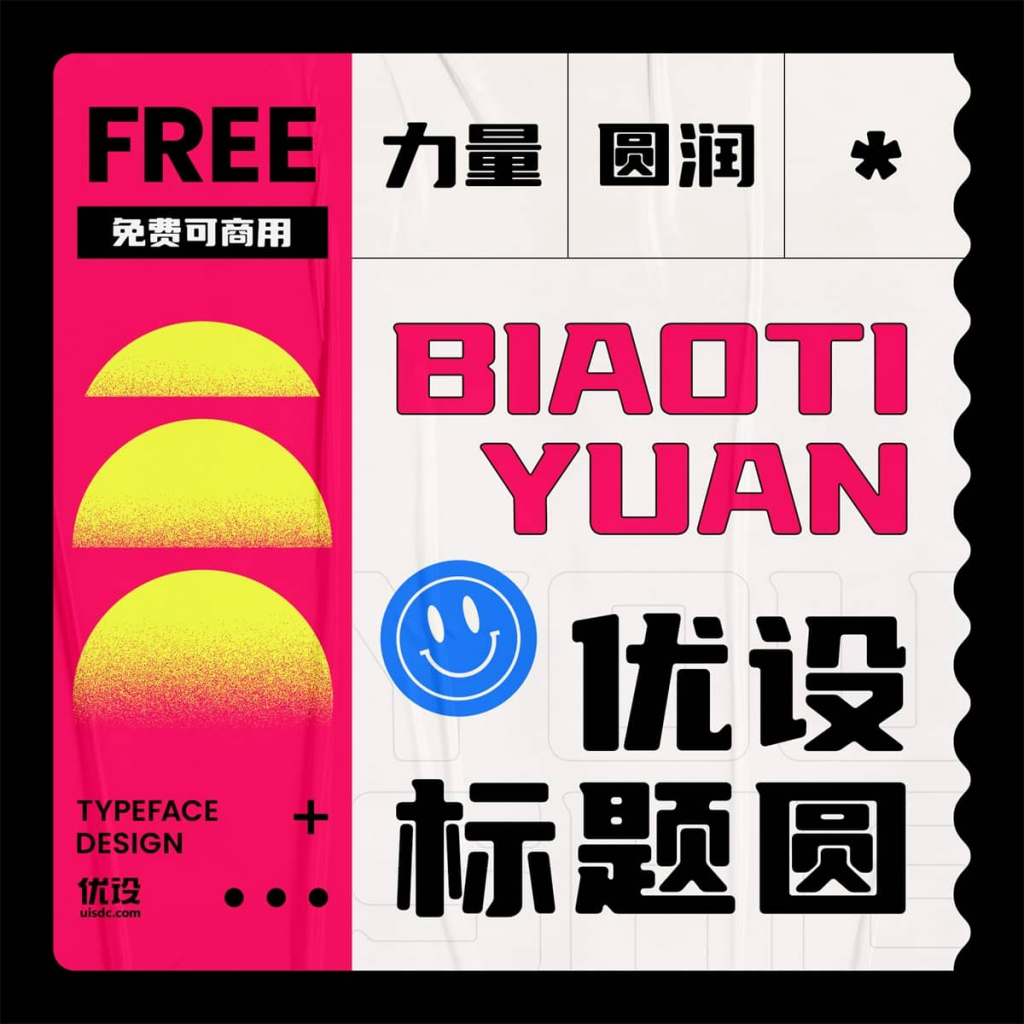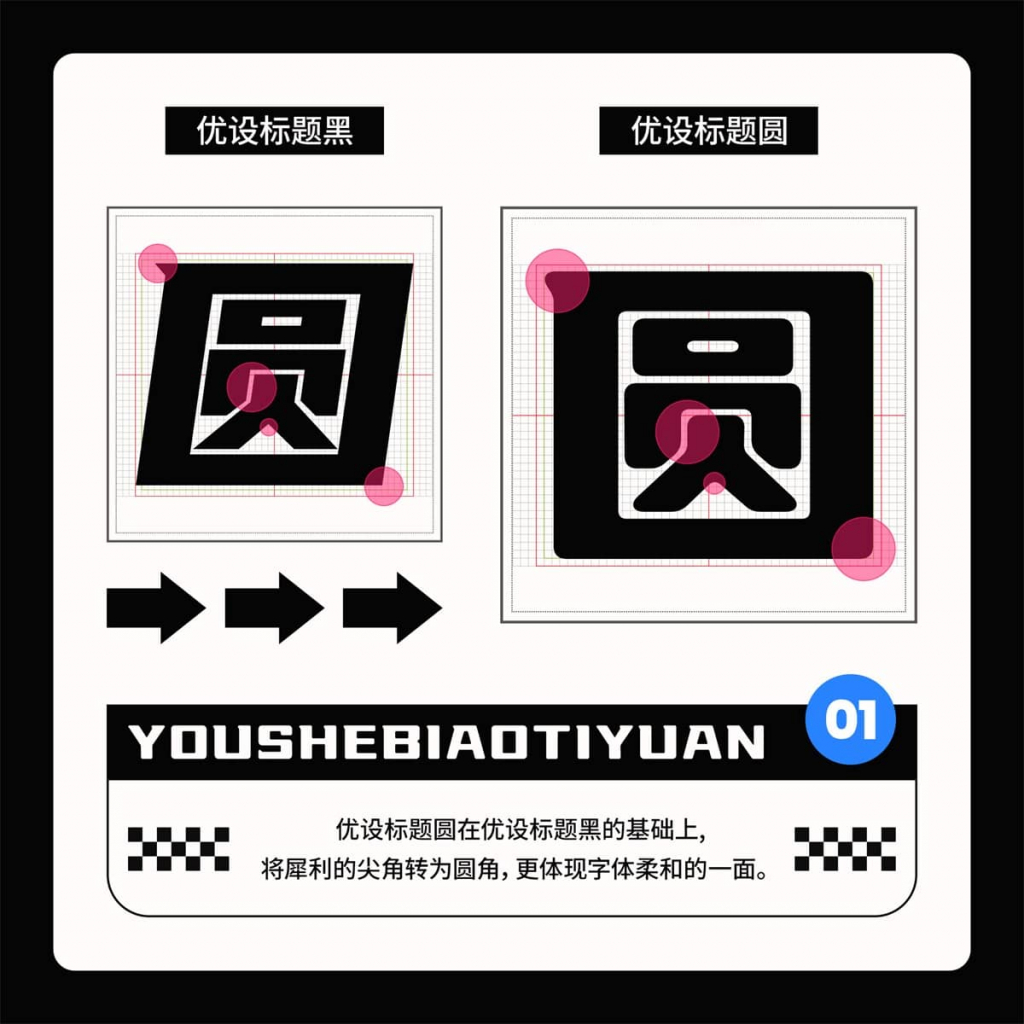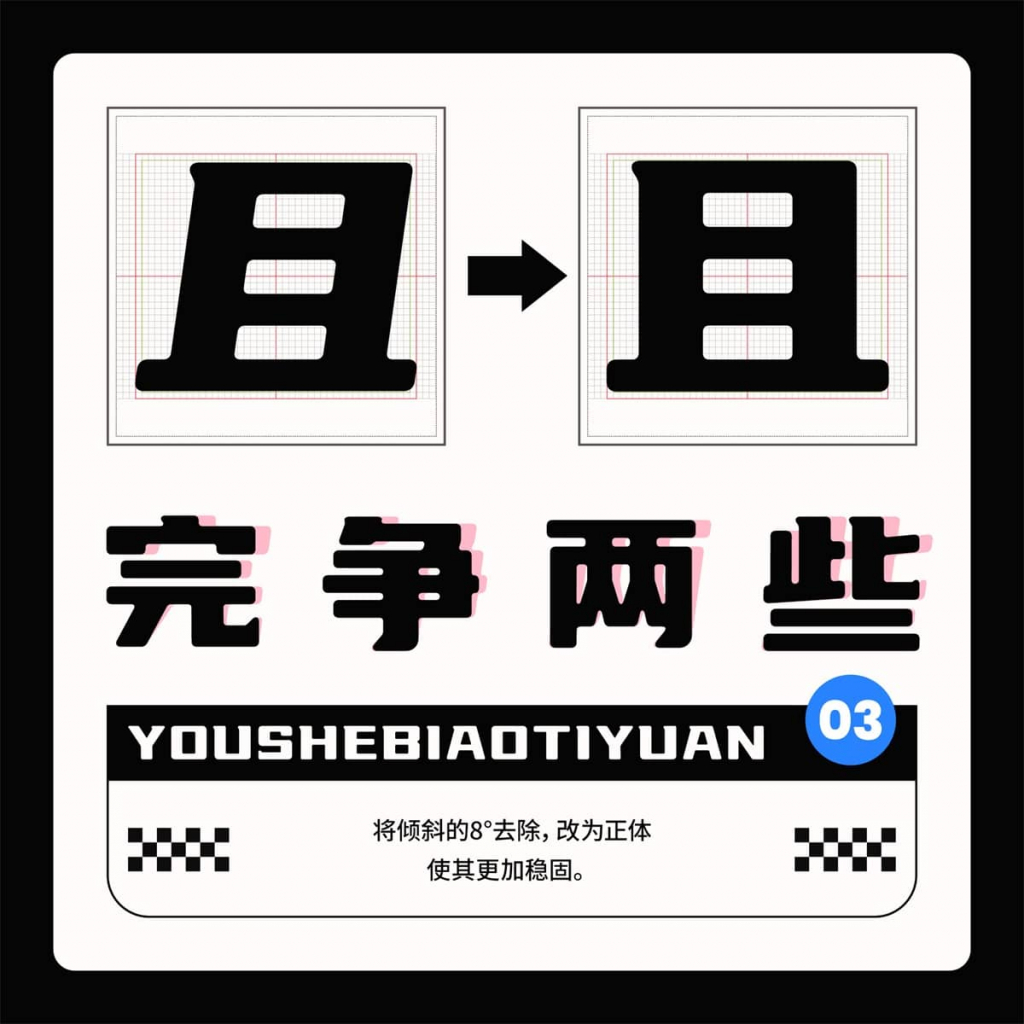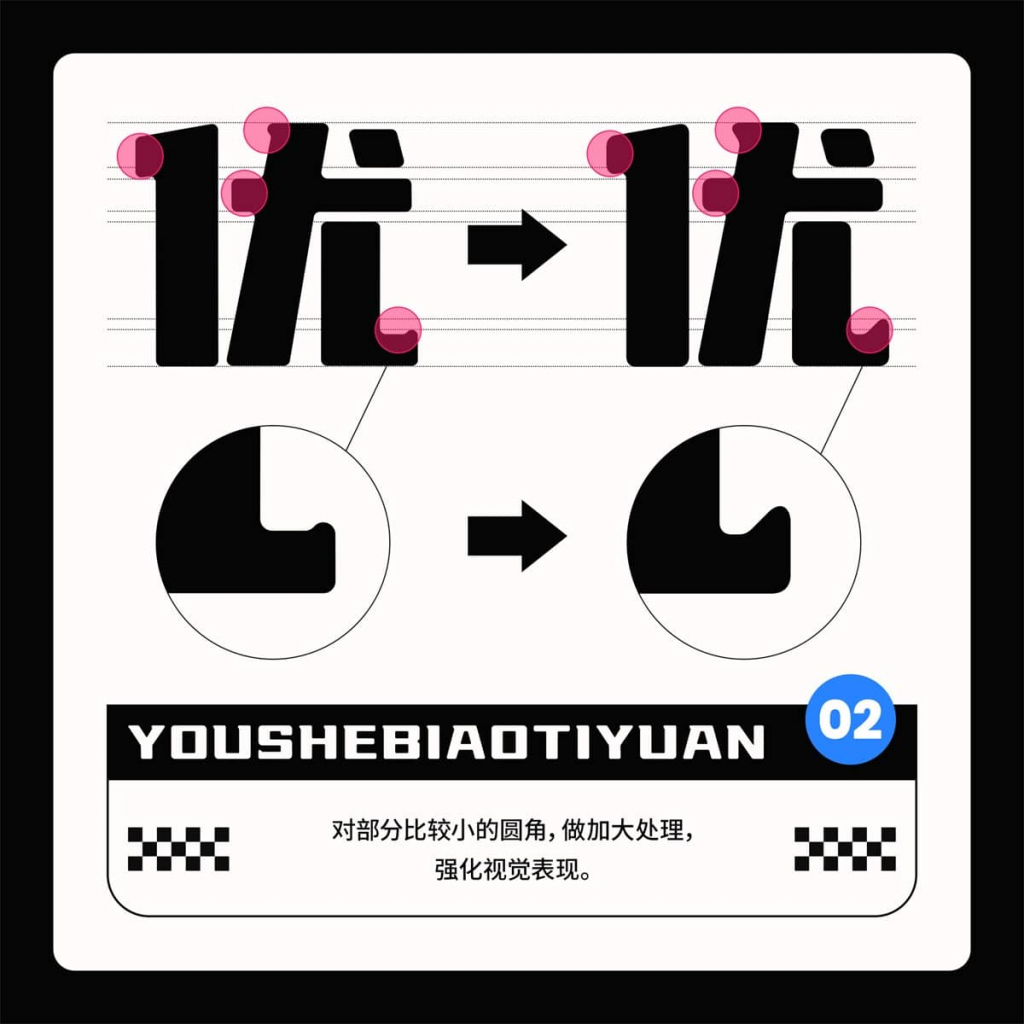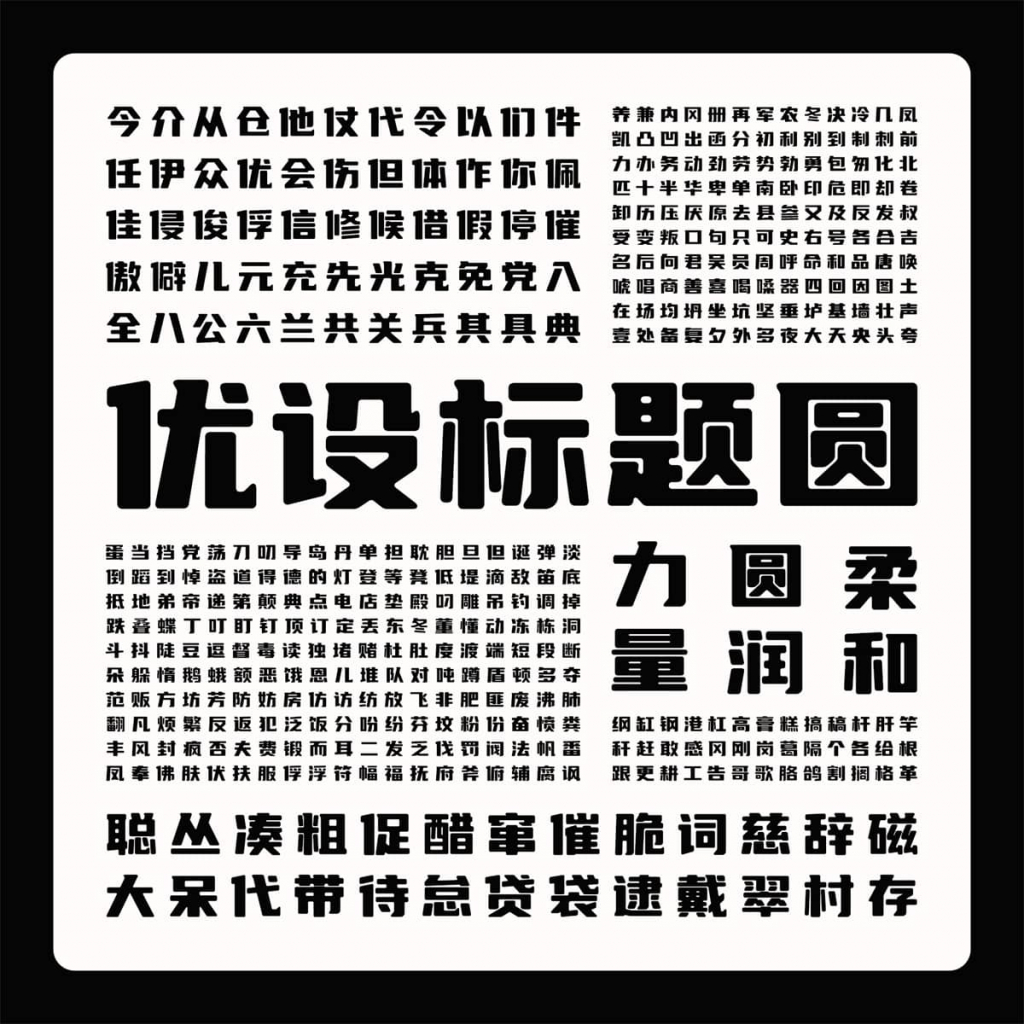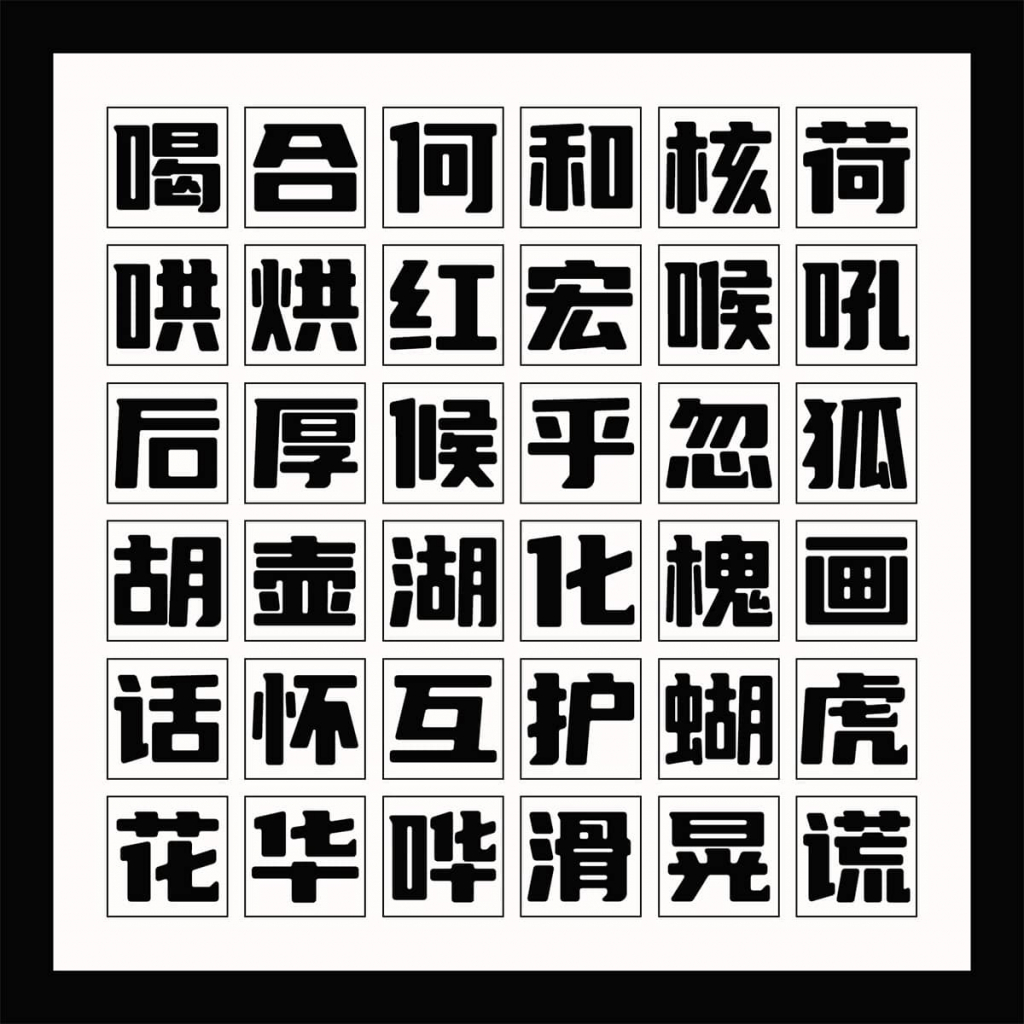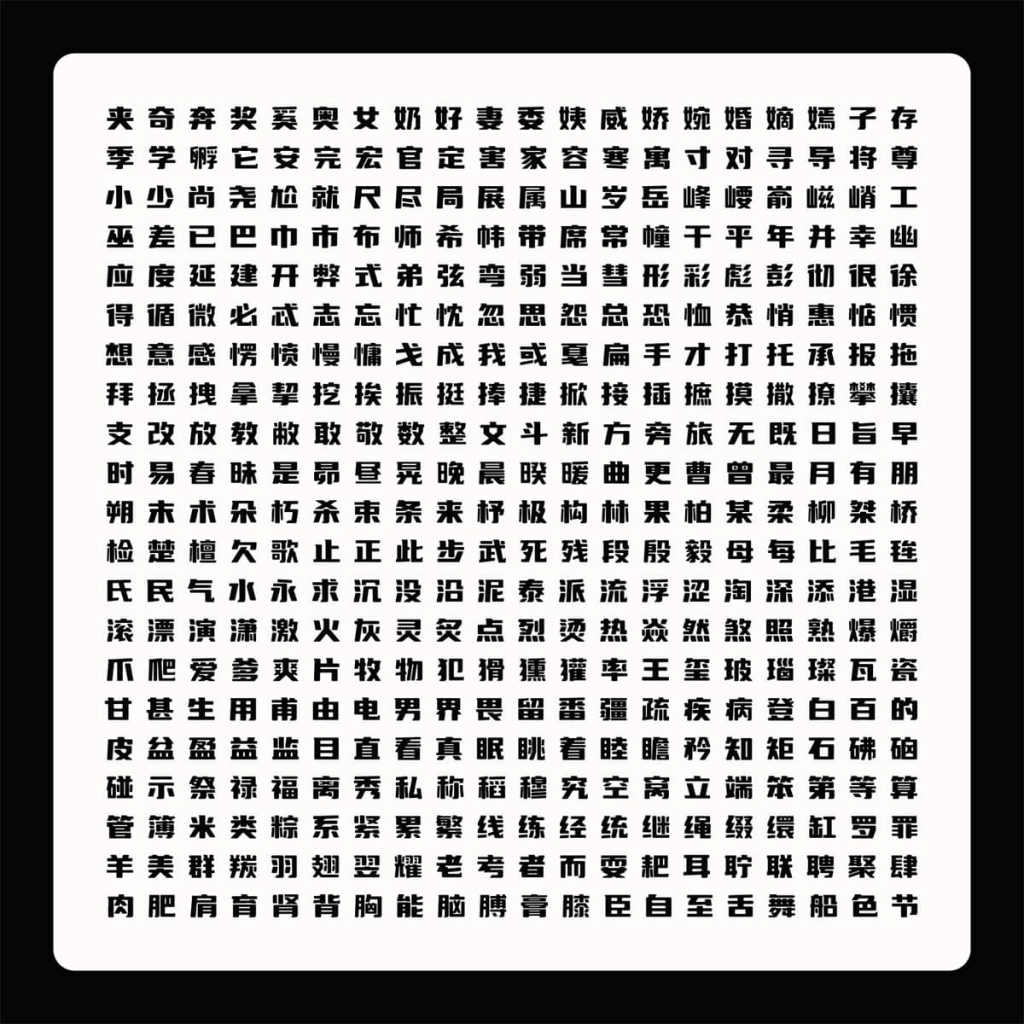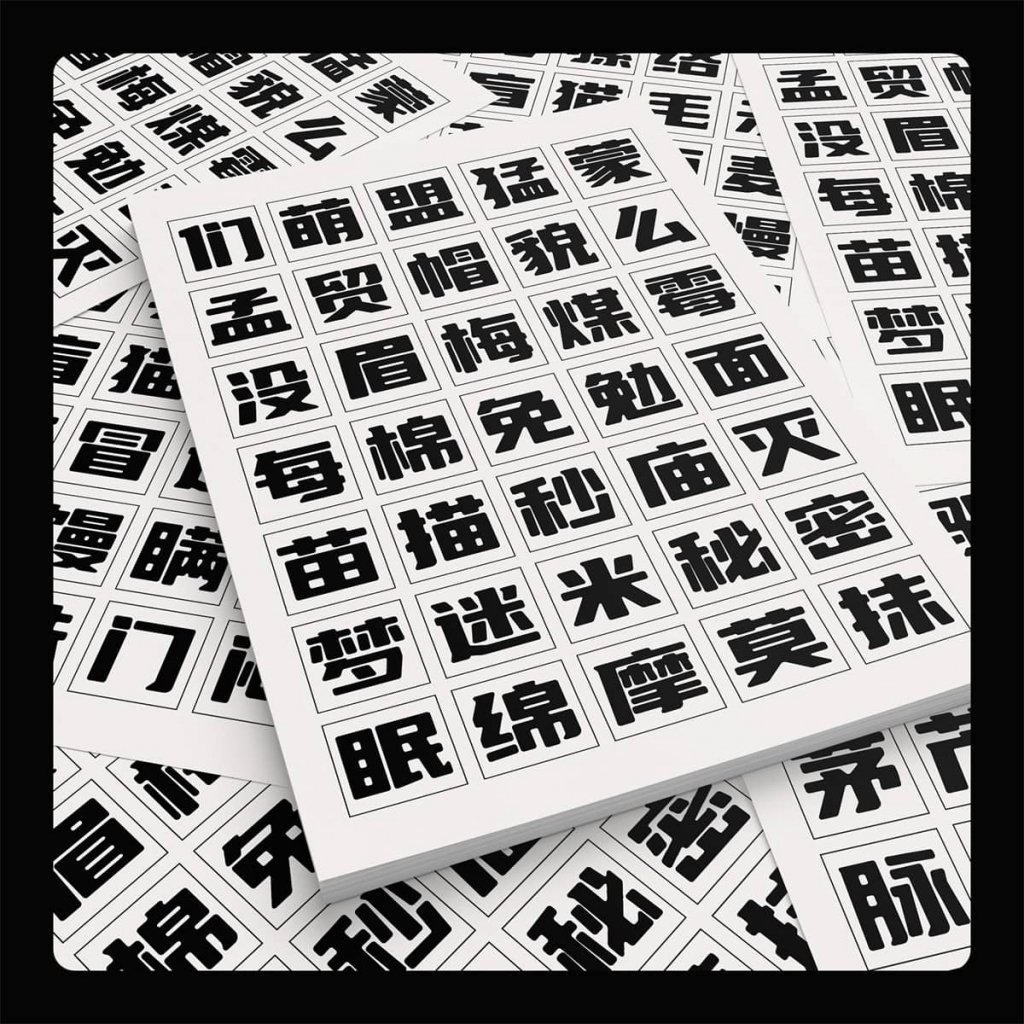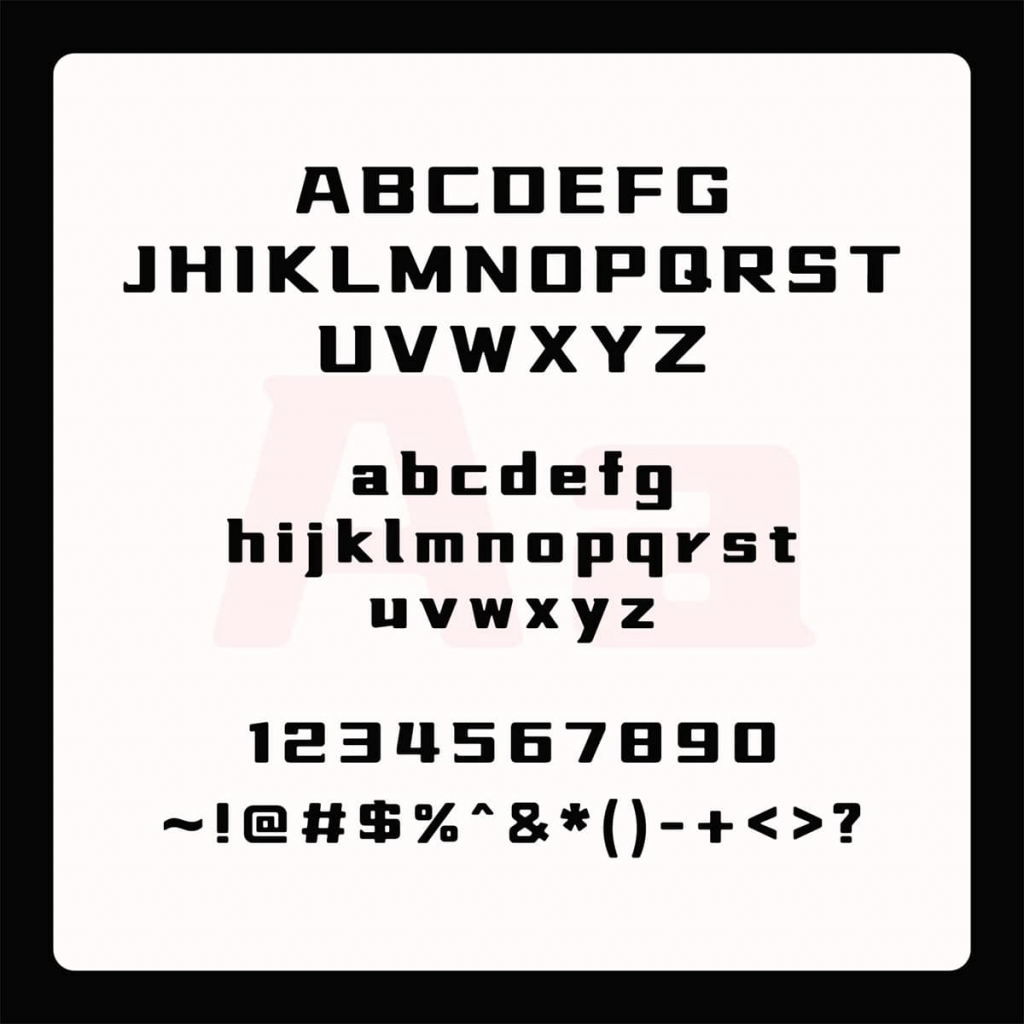
优设标题圆
从「优设标题黑」发布至今已有两年多,在这款国民级字体发布后,优设马不停蹄,集结了团队的中坚设计师,继续发布了电商领域的宠儿「优设好身体」和另一个风格可爱的「优设字由棒棒体」。
欣慰的是,这两年在各大电商平台、综艺节目和电影电视剧,甚至许多官媒里都能看到我们的字体。特别是优设标题黑,因其速度感和力量感兼具的特点,作为标题字体再合适不过,一度成为许多设计师的最爱。
优设标题圆
但这两年我们也观察到一个现象:大家在使用标题黑时,有概率会将它调正进行使用,多方调研和讨论后,我们决定在「优设标题黑」的基础上做一个全新的版本,让它的使用范围更加广泛。历经一年多的修改后,这款标题黑的升级版,也是优设第4款免费可商用的中文字体:优设标题圆。
今天正式上线啦!
优设标题圆
字体特点
作为「优设标题黑」的兄弟版,这款字体在保留「优设标题黑」的力量感的基础上,将8°倾斜去除,从斜体变为正体,减弱速度感,增加稳固的感受:
字体整体风格与标题黑形成直接对比,一个刚毅,一个柔和。